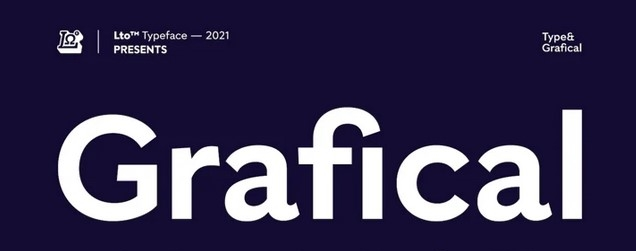
[Myfonts] Grafical Font (2021)
Название: Grafical Font (2021)
Grafical - это современный геометрический гротеск без засечек, разработанный с использованием геометрических форм, которые были оптически скорректированы для лучшей читаемости. Полностью семейство включает в себя шрифт от сверхсветлого до черного и соответствующий ему курсив, разработанный на основе элементарных форм и обеспечивающий простоту модернистского и нейтрального шрифта.